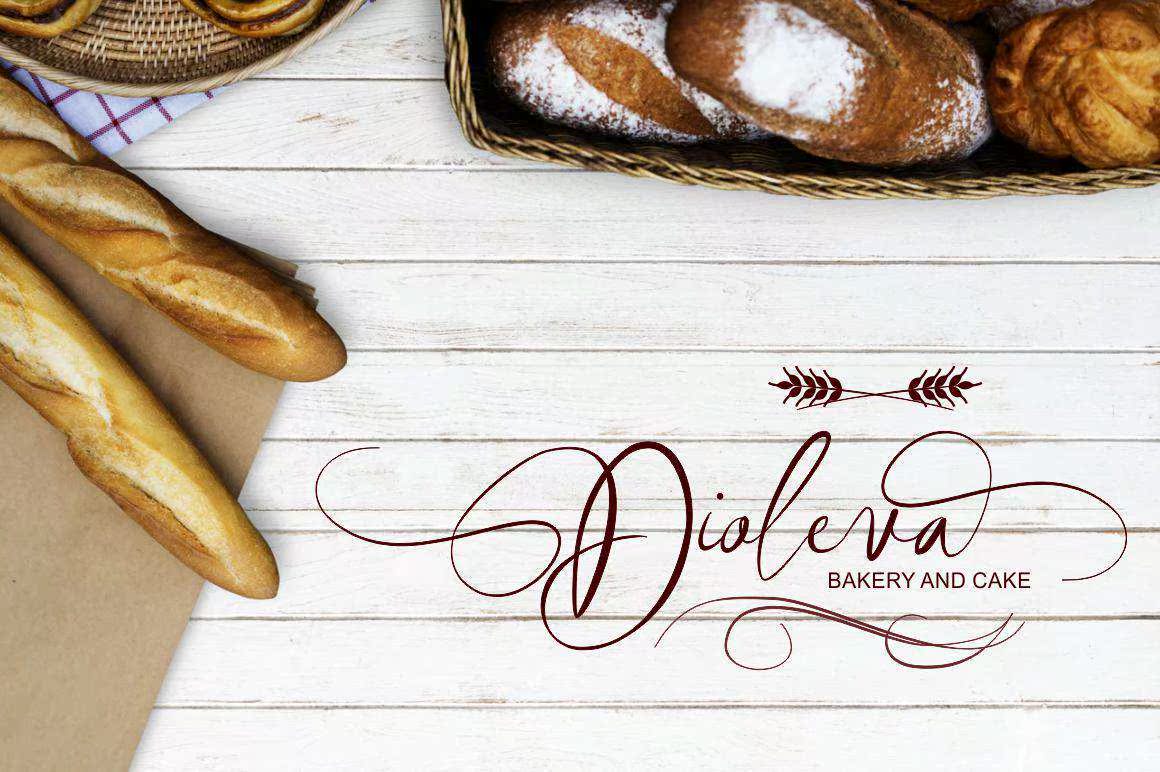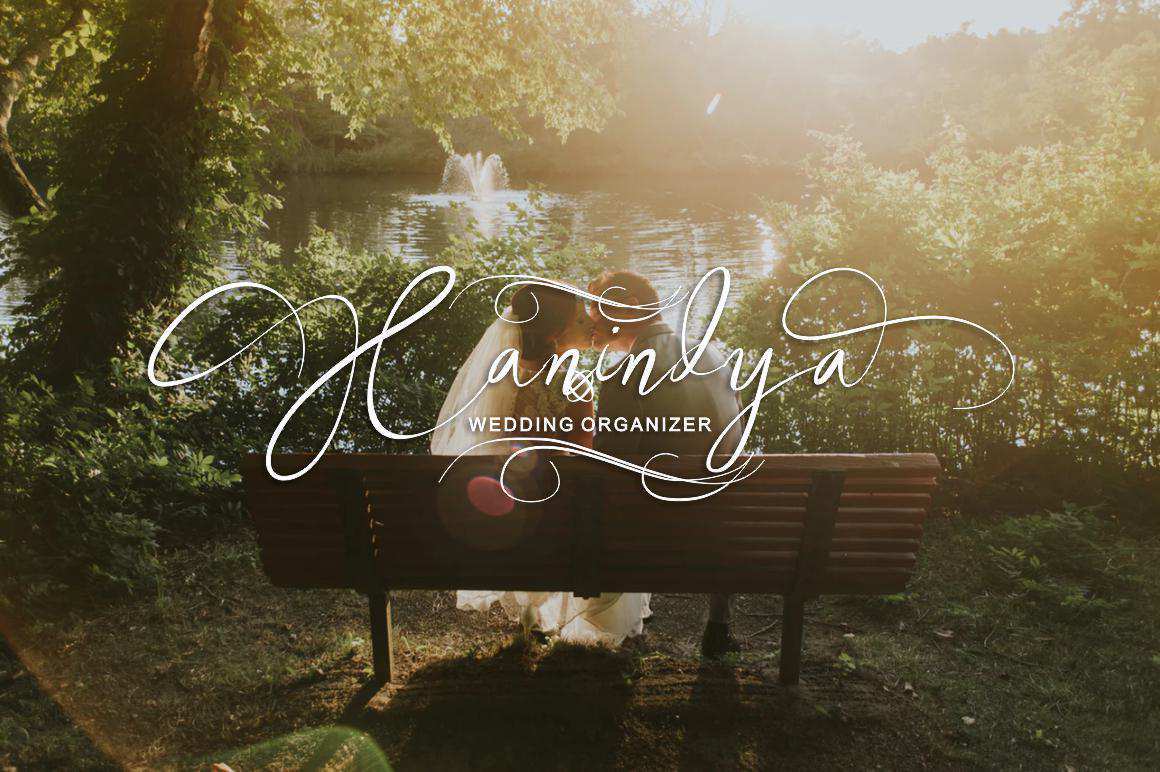
嗨,这是我的最新作品,它的思想是直接与自然结合和书写。作品看起来美丽迷人,适合于需要女性化设计。请将这部作品作为最佳收藏,如果你需要信息,不要与我接触。嗨,这是我的最新作品,该字体的设计理念是直接与自然相结合。字体看起来美丽迷人,适合于需要女性化设计主题的设计。请将此字体作为最佳收藏,如果您需要信息,请不要与我联系。